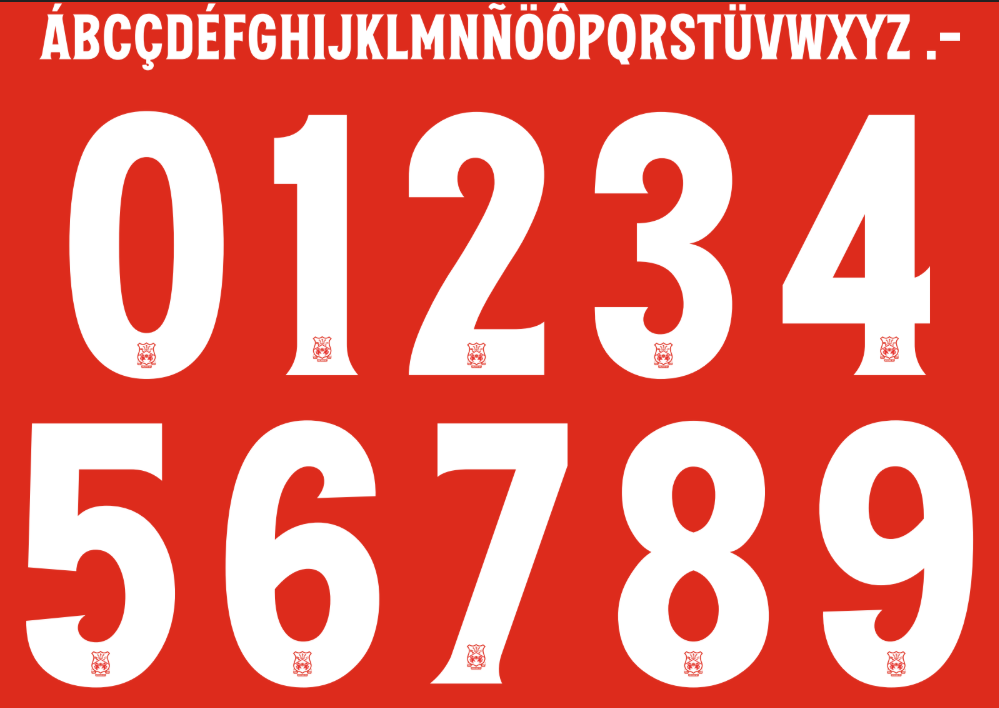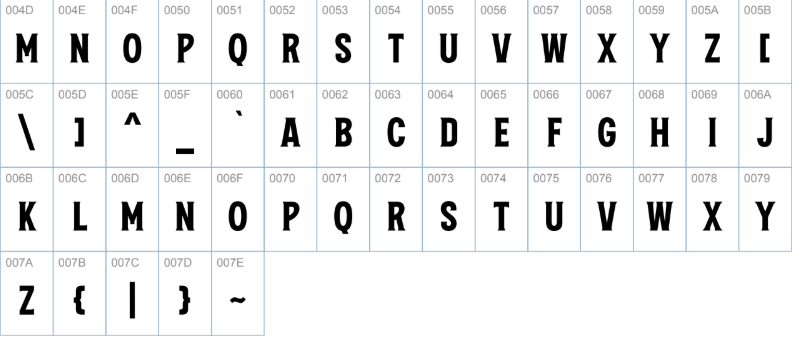
A tipografia é uma parte crucial dessa nova identidade visual. Com o clube ganhando visibilidade na ESPN e em plataformas de streaming global, a fonte utilizada nas camisas (especialmente em jogos de Copas ou edições especiais que fogem do padrão da liga) precisa transmitir força e tradição. Ter esse arquivo em mãos é essencial para designers que querem surfar na onda do “efeito Wrexham”.
Estilo visual da tipografia
A fonte desta temporada reflete o momento ambicioso do Wrexham AFC. Diferente das fontes genéricas, esta tipografia busca um equilíbrio entre o estilo industrial britânico e a modernidade exigida pela Macron.
- Design: A fonte apresenta caracteres sans-serif robustos e condensados. As letras possuem vértices levemente arredondados, mas mantêm uma estrutura sólida e imponente, facilitando a leitura à distância e na TV.
- Aplicação: Nos uniformes oficiais, a numeração geralmente aparece em branco (no kit Home) ou em vermelho/preto (nos kits Away e Third), criando um contraste forte.
- Identidade: O estilo visual remete à determinação e ao trabalho duro da comunidade de Wrexham, alinhando-se com a estética dos patrocinadores máster, como a United Airlines. É uma fonte que funciona muito bem tanto em caixa alta (nomes) quanto nos números grandes das costas.